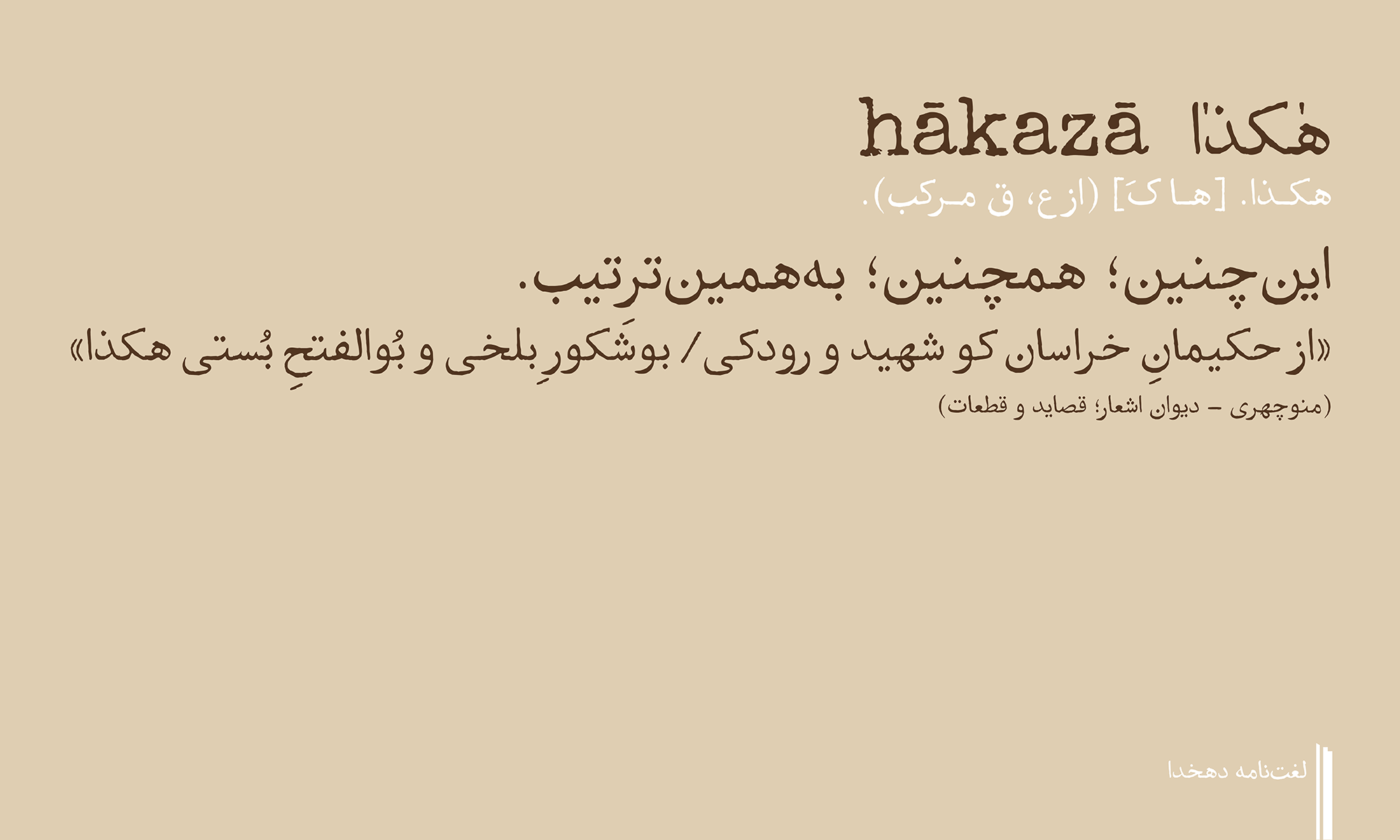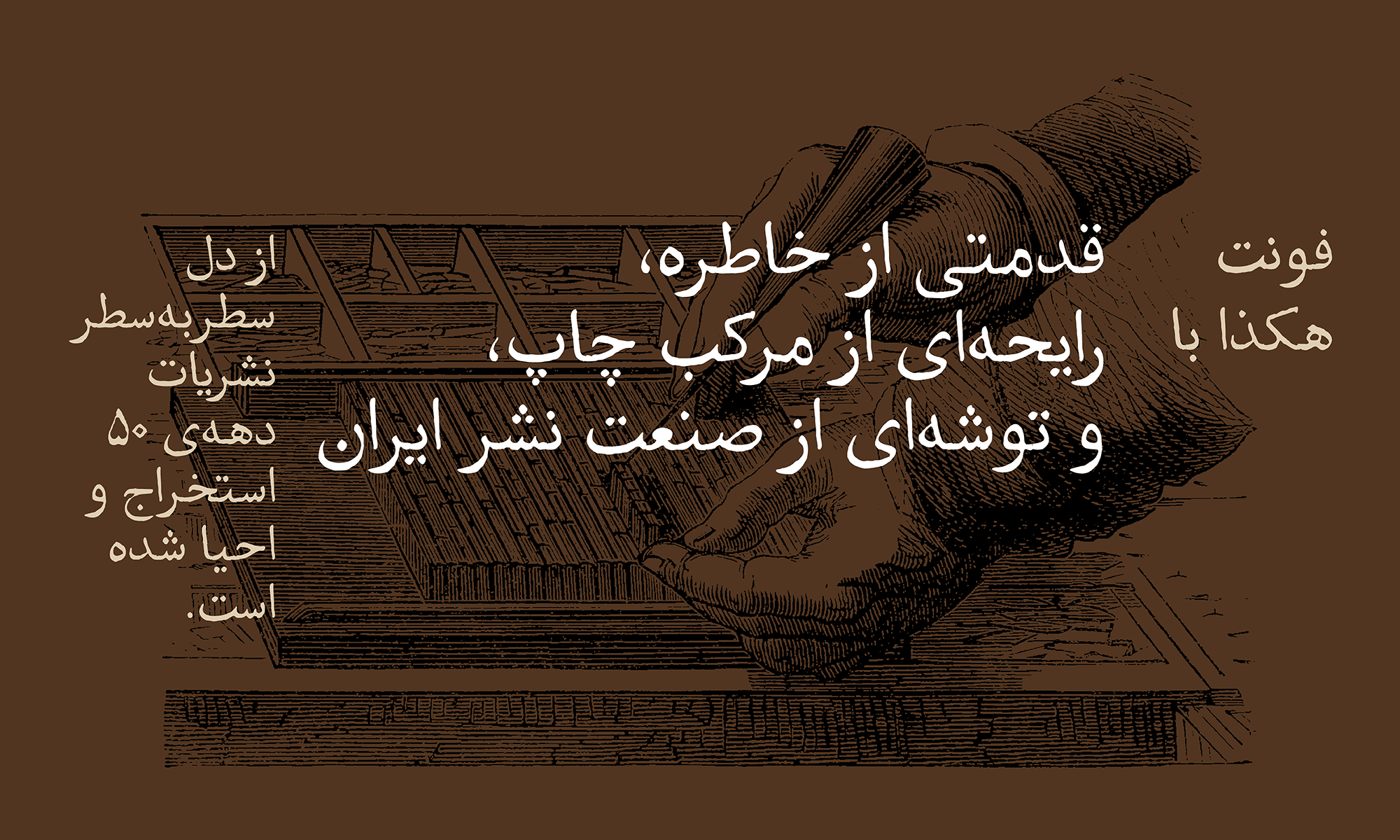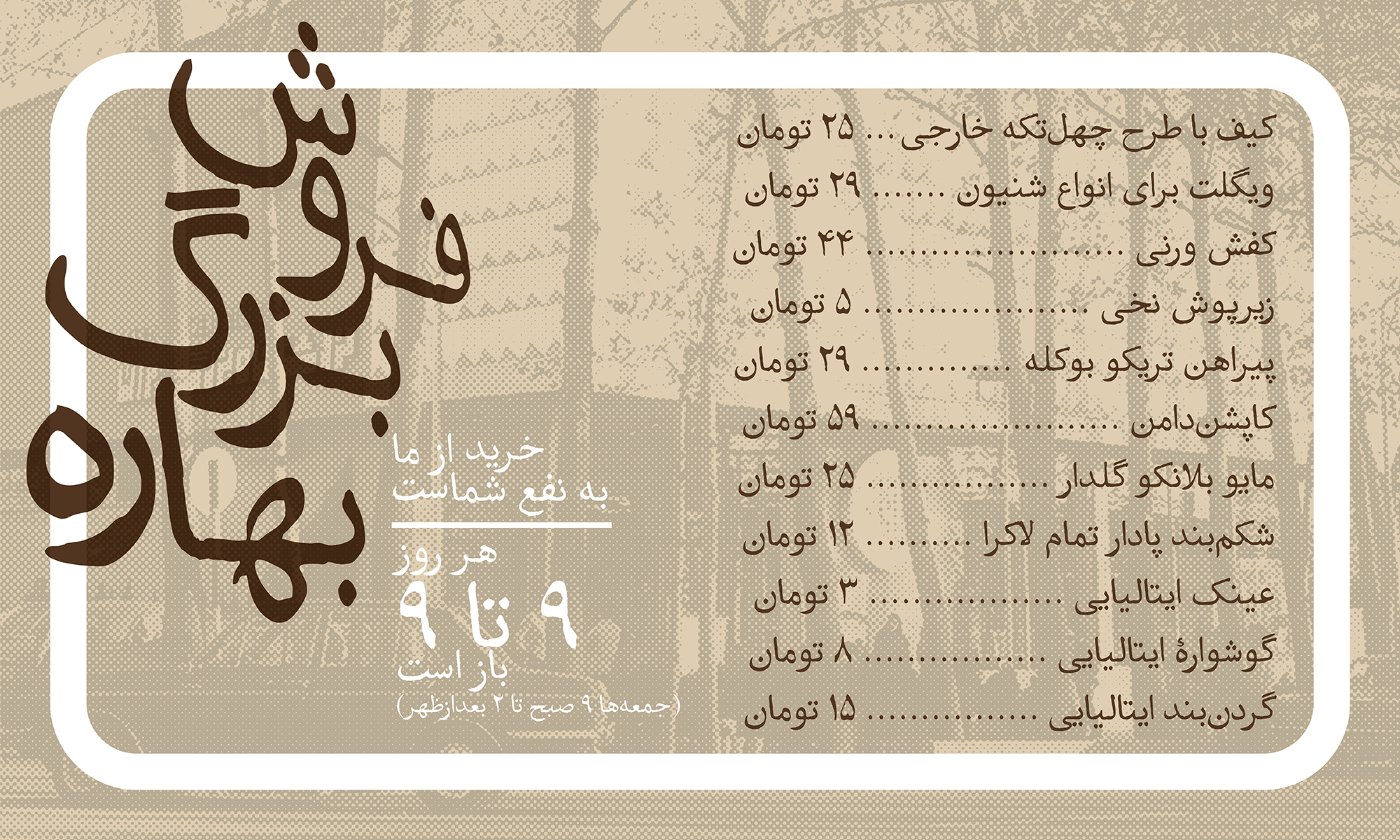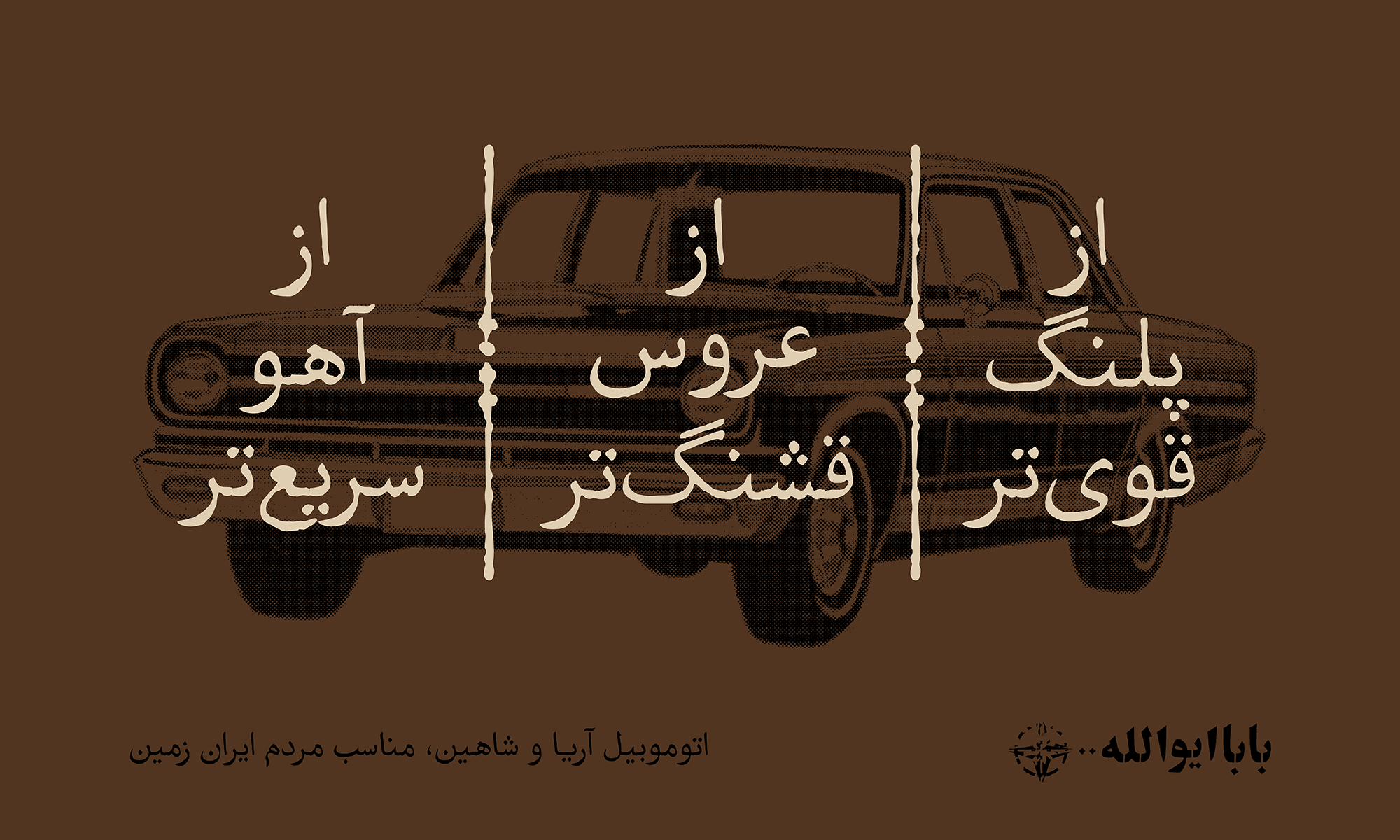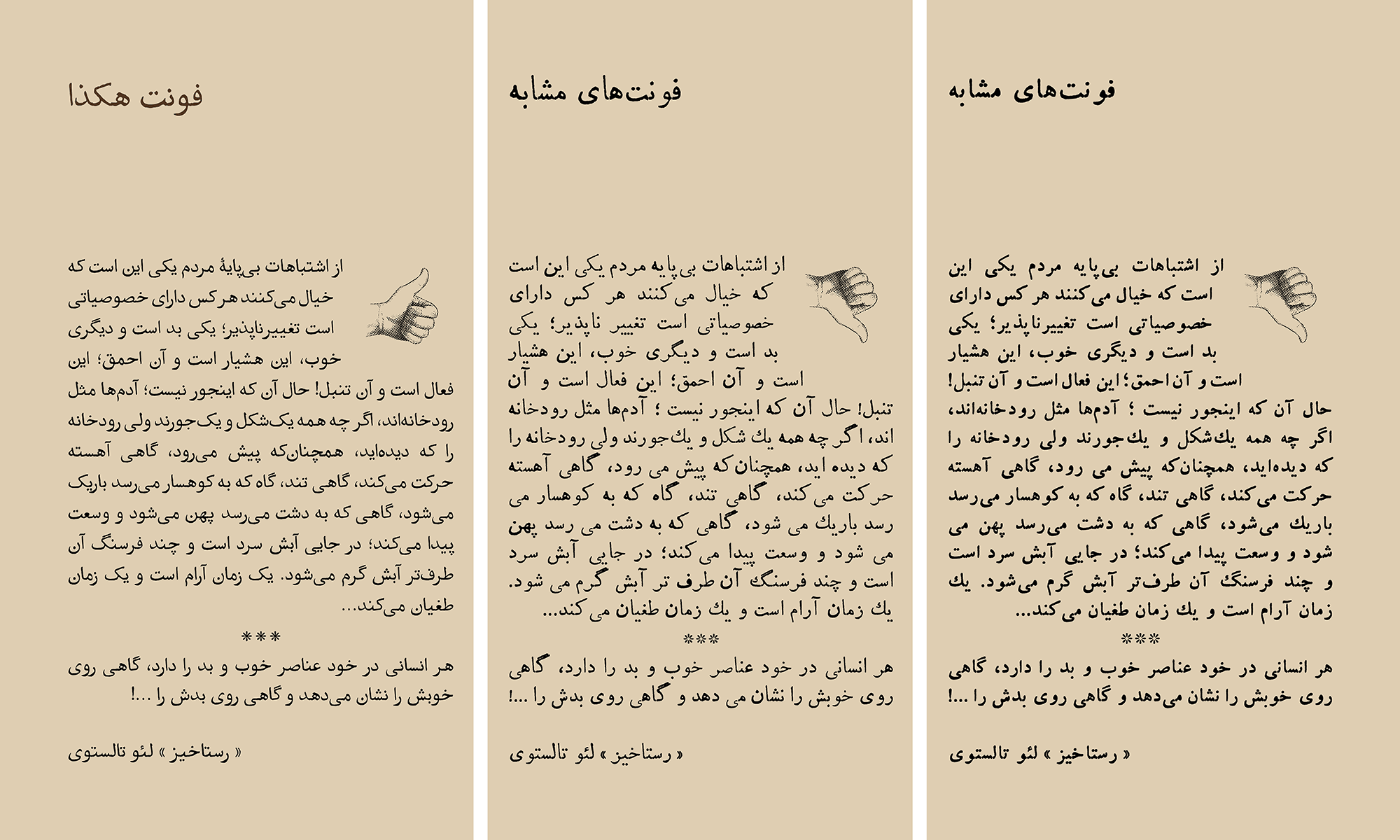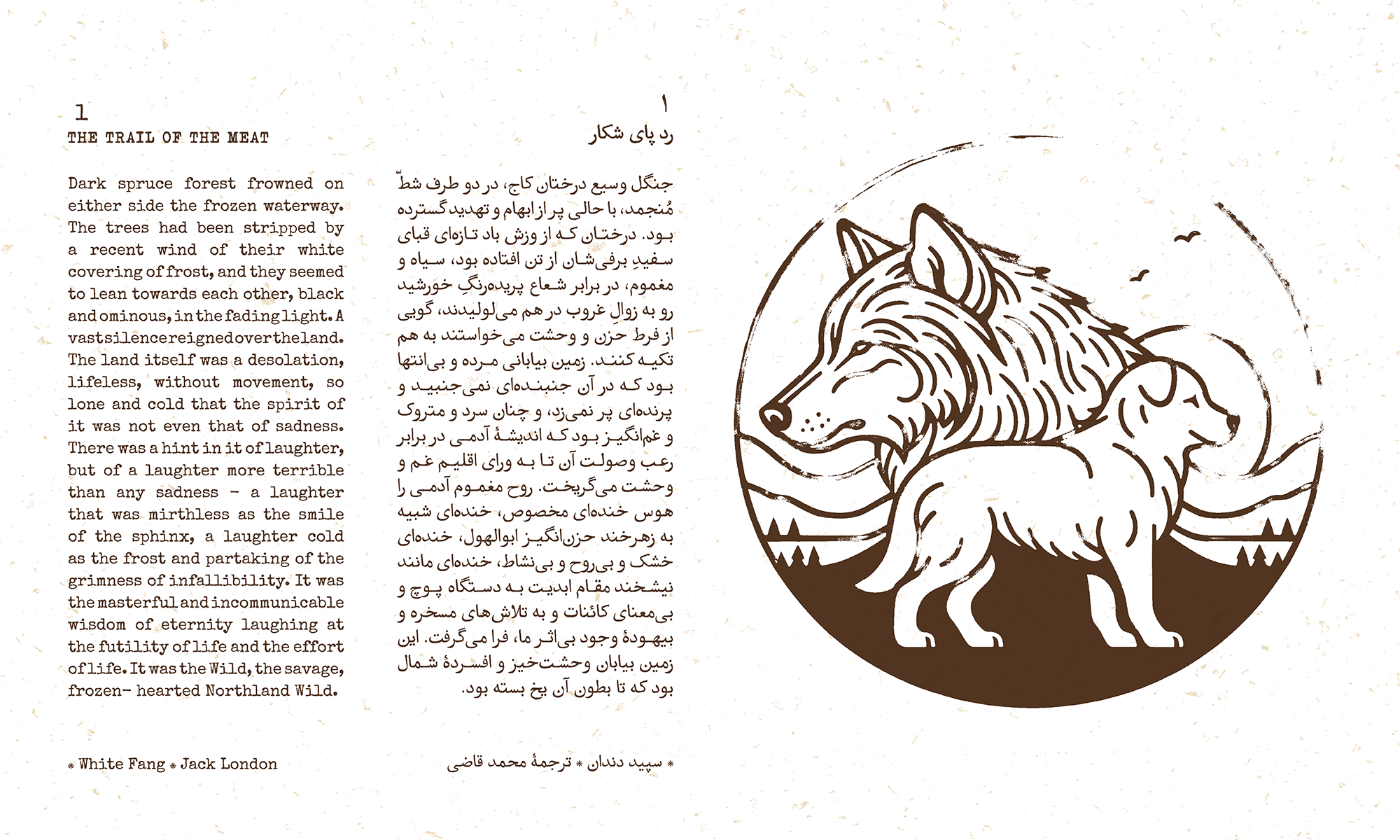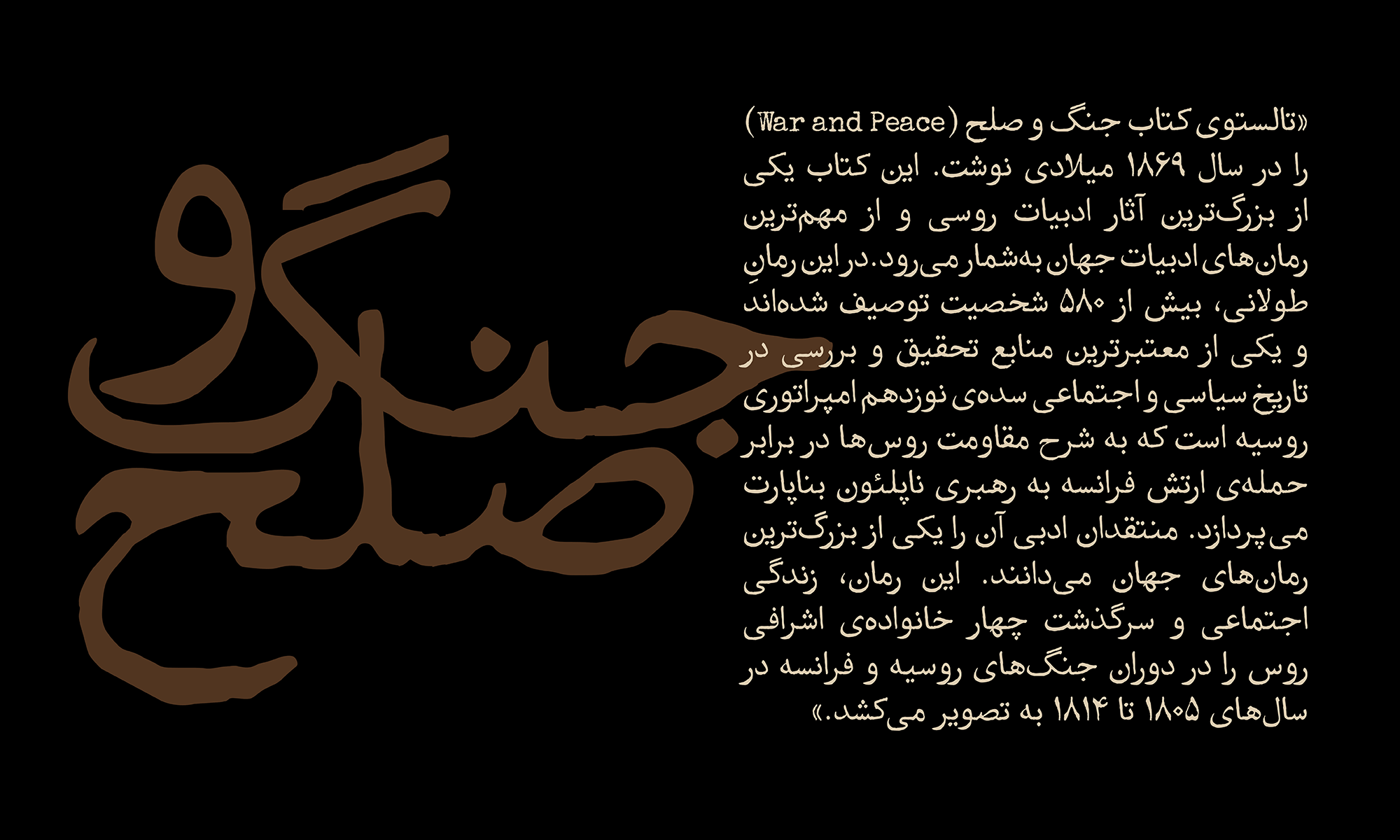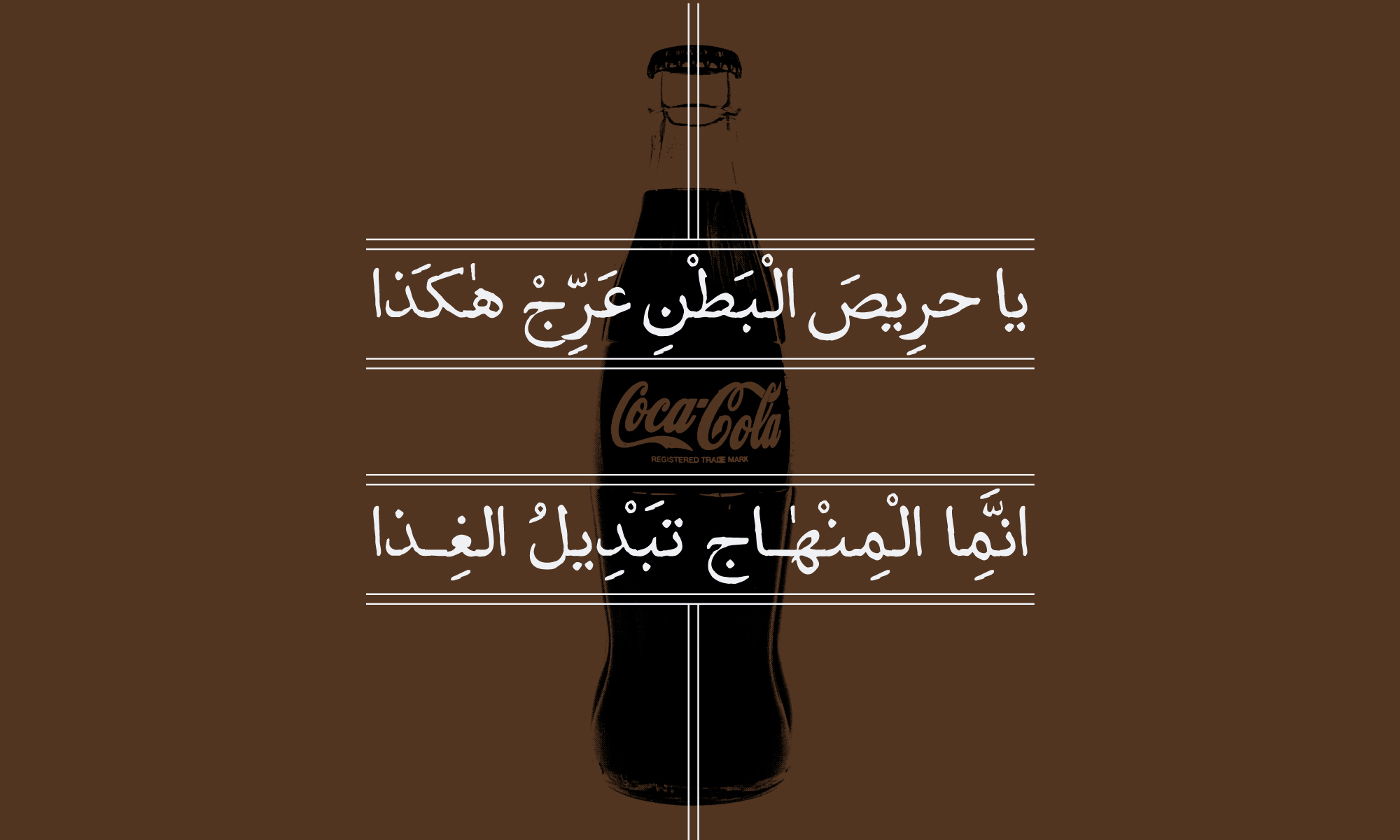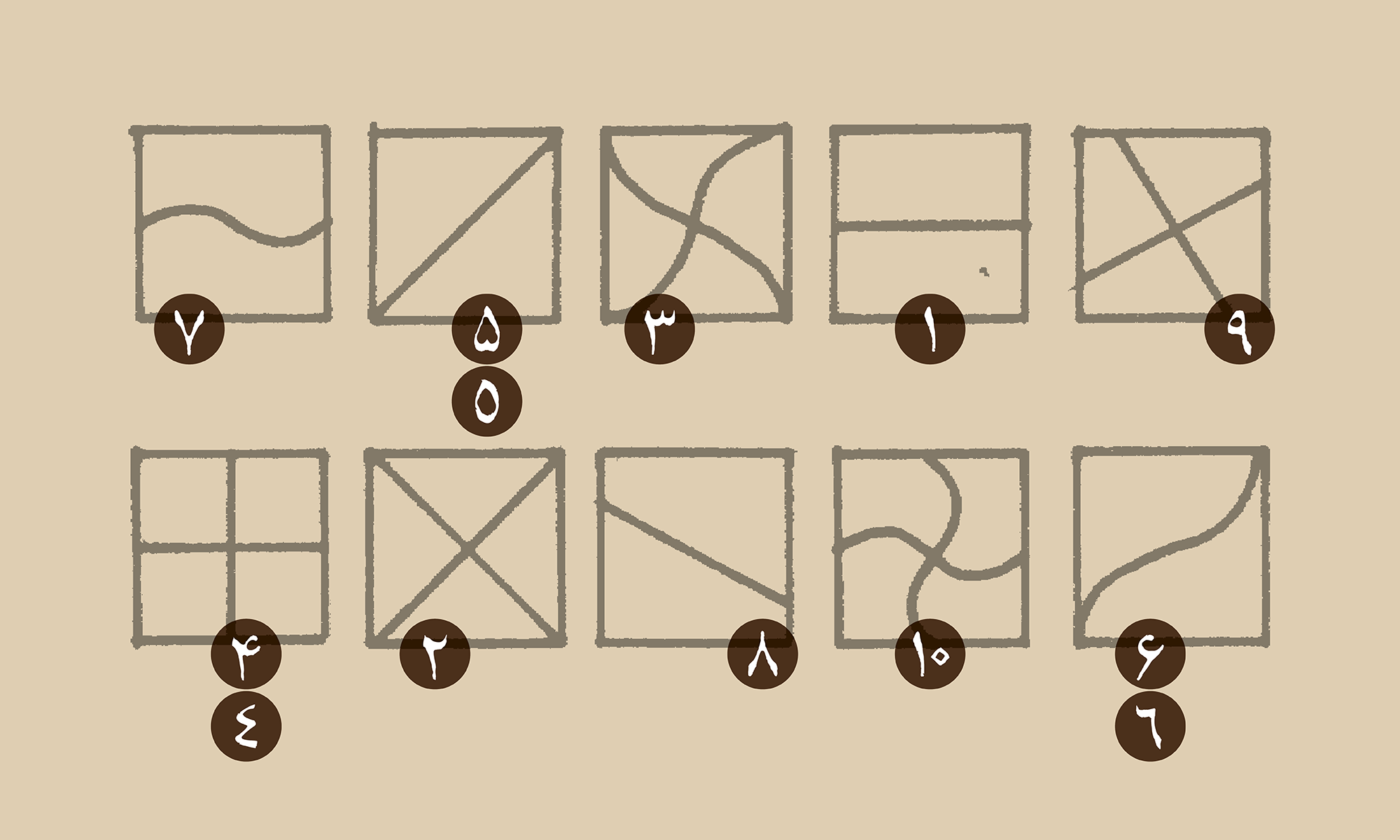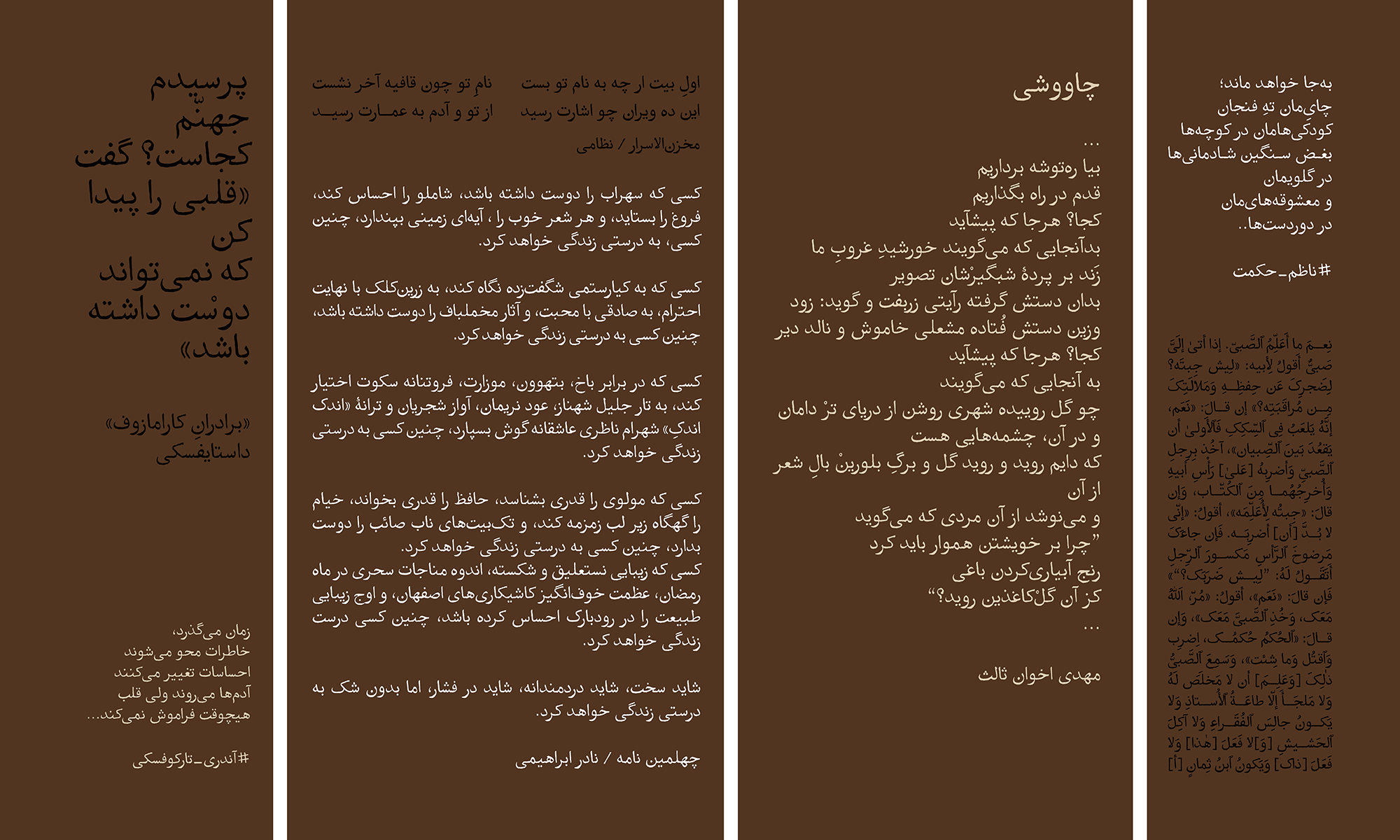
فونت هاکذا تمام هموغم خود را گذاشته تا با اصلاح و مدیریت فضاهای مثبتومنفی قلم و همچنین کرسیِ منظم حروف و حتی نقطهها، تجربهای لذتبخش و خاطرهانگیز برای خوانندهی کتاب و نشریه به ارمغان بیاورد.
متین، موقر، فرهیخته و داناست، پا به سن گذاشته اما با جوانترها نشسته. قابل اعتماد است و هر سخنی از او قابل پذیرش است؛ حتی دروغ!.
در میان معدود همنوعان خود، از فاصلهگذاری مهندسیشده و مناسبِ حروف و کلمات، و متناسب با فیزیک فونت برخوردار است (نمونههای زیر را بهدقت مقایسه کنید)، مضاف بر آن، ویژگیِ حفرههای سالم و مدیریتشدهی حروفِ هاکذا، این حُسن را نیز دارد که در متنهایی با سایزهای کوچک حتی در چاپ، روی کاغذهای بالکی، به اصطلاح پُر نمیکند.
دو سال پس از ارائهی نسخهی هاکذای سپید (رگولار) و دریافت بازخوردهای دلگرمکننده در آثار طراحان گرافیک و بازار نشر، نیاز به وزنِ هاکذای سیاه (بولد) بیش از پیش احساس شد.
بنابراین، استخوانبندی هاکذای سیاه بر اساس آناتومی نسخهی سپید طراحی شد و پس از تستگیریهای متمادی، توسعه یافت.
فونت هاکذا همنشینی بیدغدغه و صلحآمیزِ کلمات فارسی و انگلیسی در کنار یکدیگر را فراهم آورده است تا کاربر فقط با تغییر زبان کیبورد خود، از این امکان در متن مورد نظرش بهره ببرد؛ با این ویژگی که هر دو از یک جنس و فرم نیز هستند.
فونت هاکذا در قالب پاراگراف متن، ستونهای روزنامهای و نیز در قالب عنوان و تیتر اصلی کتاب و مجله قابل استفاده است. بنابراین دست طراح یا کاربر برای بهرهبرداری خلاقانه از فونت کاملاً باز است.
در طی پروسهی آمادهسازی فونت هاکذا به دغدغههای ریز و درشت همهی افرادی که با متن، فونت و دیزاین سروکار دارند اندیشیده شده است تا بهرهبرداری از آن را برای کاربرش آسانتر و بیدغدغهتر از نمونههای مشابه کند.